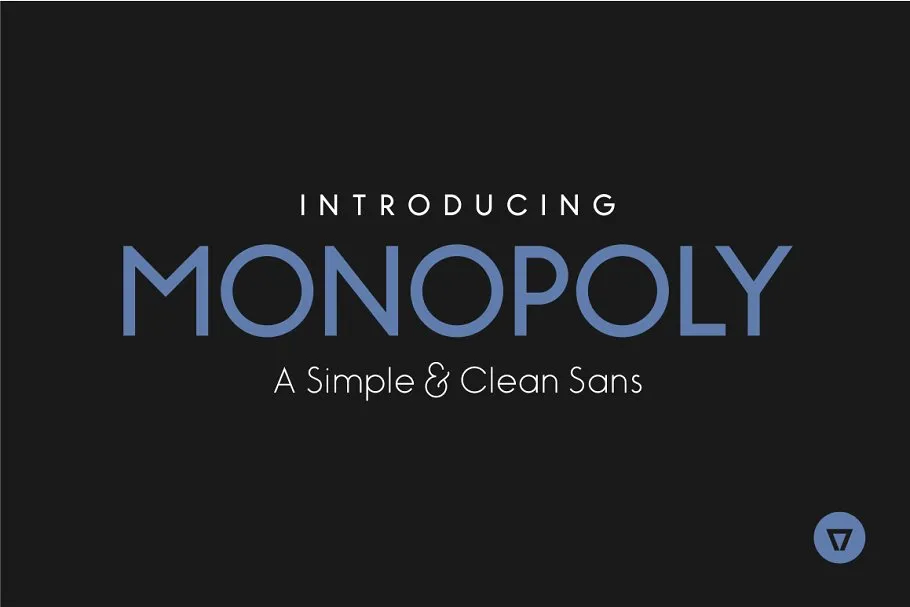
A Monopoly Sans é uma elegante e clara fonte de sans-serif projetada para atender a diversas necessidades de design. Com sua aparência moderna e limpa, ela é ideal tanto para trabalhos impressos como digitais. Esta fonte vem com três opções de estilo: Líquido, Bold e Bold Inline, proporcionando aos designers o poder de adaptar-a a um vasto espectro de projetos. Suporte completo em caracteres da língua inglesa e internacional faz dela uma escolha versátil para trabalhos como posters, design web, identidade corporativa, ilustrações ou qualquer outra aplicação que você possa imaginar. A Monopoly oferece um toque único de originalidade a cada projeto, tornando-a uma excelente escolha para designers em busca de algo novo e moderno no seu arsenal de fontes.